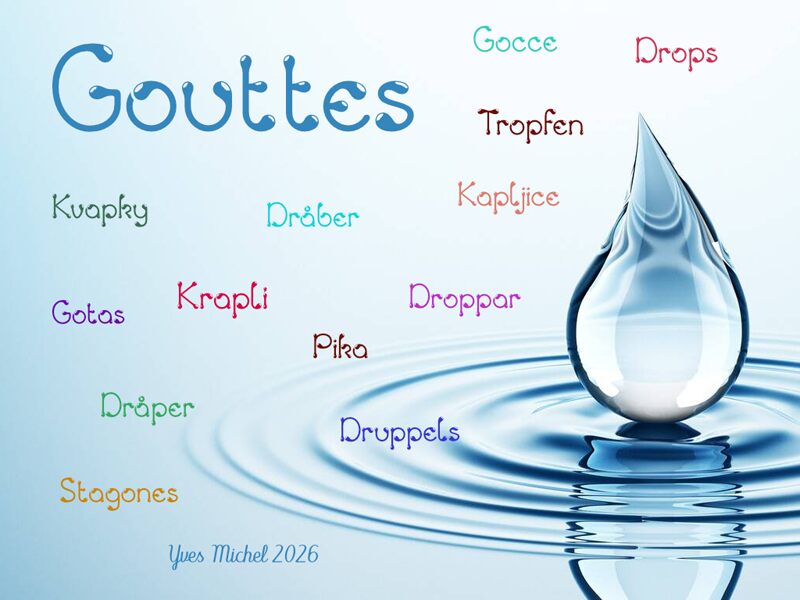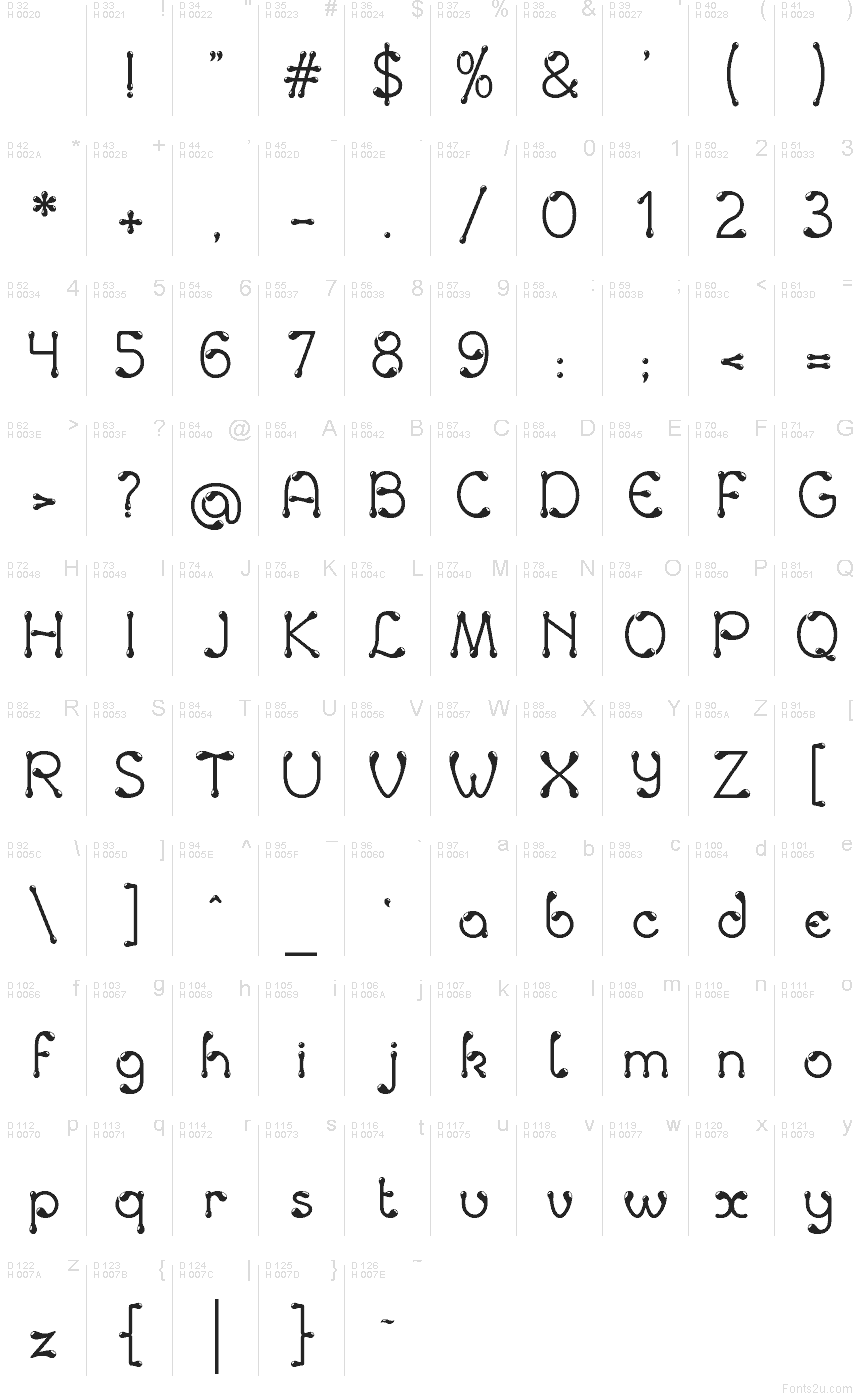
Gouttes Medium
Gouttes od Yvese Michela je bezplatné dekorativní display písmo ve tvaru jemných, protáhlých kapek. Jeho štíhlá písmena se na koncích rozšiřují a drobné výřezy světelných odlesků dodávají zaobleným tahům mokrý, sklovitý povrch.
Voda, kosmetika, sladkosti a hravá vědecká témata představují pro toto plynulé písmo přirozené prostředí, zejména na obalech, plakátech a vizuálech pro akce. V časopiseckém designu dokáže proměnit titulní nápis v součást ilustrovaného cákance nebo tekutého motivu.